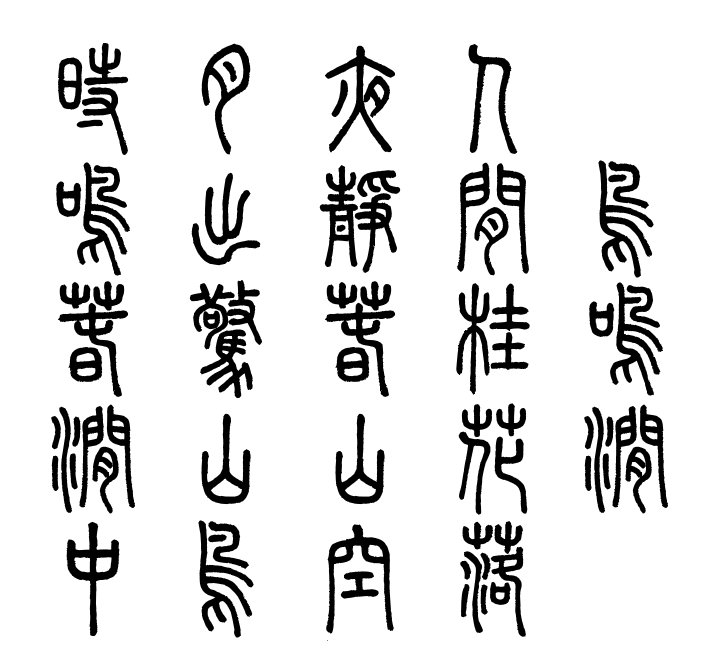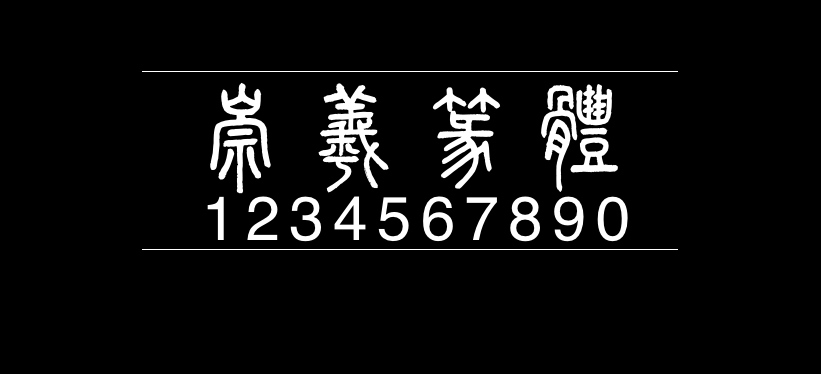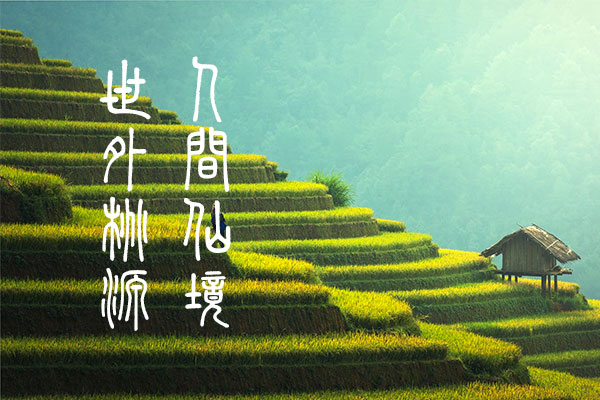
崇羲篆体
崇羲篆体由于是台湾网友创作发布的,所以对繁体中文支持的不错,简体中文则存在一些缺字的现象,这也很正常,因为这款字体本来就偏古风,而中文古风字体就没有用简体字的,否则会不伦不类。
以下是对字体发布介绍信息的原文引用:
小篆是汉字的优秀字形 ,是人类文明的瑰宝,二千年来,深受广大人民的喜爱。
小篆字形以《说文解字》为依据,《说文解字》虽然有一些板本的差异,但在文字学家的努力之下,绝大部分已取得一定的共识,问题不大。问题最大的是《说文解字》未收字,或《说文解字》之后产生的汉字。这些字没有篆体,广大的小篆喜爱者深感苦恼。历代书法家也个别为一些字转写为篆体,但是没有全面系统化的进行,也未能进入现代的电脑字型,所以当代的使用者无法享用到这些成果。也有电脑字型公司完成了全套的篆字字型,但是并未请教文字学家,所以成品难以过关,如“有”字写成“”、“为”字写成“”、“丢”字写成“”等,都是让人无法理解的形体。
王心怡女士学习小篆逾三十年,在台师大、北师大学习文字学,又花了很大功夫编制《商周图形文字编》,认认真真的把文字学专业学习通透。她有特殊的感受力,感受到上天要她完成篆字的书写。而一向对电脑中文关心备至的谢清俊教授也提议要开发一套适合各界使用而又合于文字学专业要求的全篆字,在各种因缘具足的条件下,心怡欣然接受了这个任务。在谢教授的领导下,庄德明先生和我义无反顾的加入了这个行列。经过三年多的努力,这个工作基本完成了,令人欣慰。
崇羲篆体的制作体例,文字学方面的说明如下:
1. 字数儘量求多,常用字、次常用字、罕用字、异体字,只要是典籍、文学、生活常用到的字,儘可能的收入。
2. 见于《说文解字》的字,依大徐本《说文解字》的形体书写。大徐本《说文解字》的板本差异,依据相关条件择其善者从之。
3. 大徐本《说文解字》同一个字,作为单字与作为偏旁时往往会有些微的差异,作为偏旁时也往往并不全同,如:“”、“”、“”、“”四字的“亢”就不相同,这其实反映了文字流传中的实际情况,本字型完全依大徐本《说文解字》书写,不予更动。而在书写大徐本《说文解字》未收字时,则依单字字样书写,如:“”、“”。
4. 不见于大徐本《说文解字》的字,依据合理的字形结构,採用《说文解字》的小篆偏旁转写。如“牀”字,《说文解字》作“”,从木丬声。但是坊间都写成“床”,标准字体也规定作“床”,《干禄字书》已经指出这是个俗字,崇羲篆体也只能依据俗字从广从木写成“”。
5. 有些后起字的结构难以考订,或众说不同,只能择善而从,无法求备,如“丢”字,《字彙》释为“一去不还也”,或以为从“去”,“丿 ”为指事符号。二说皆有理,姑从《字彙》旧说作“ ”。